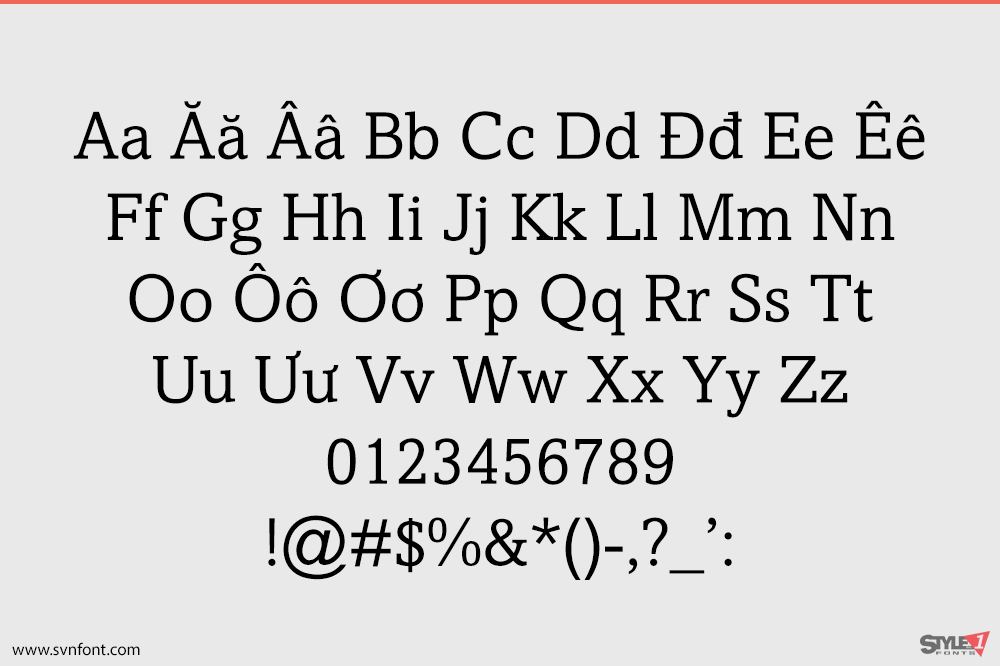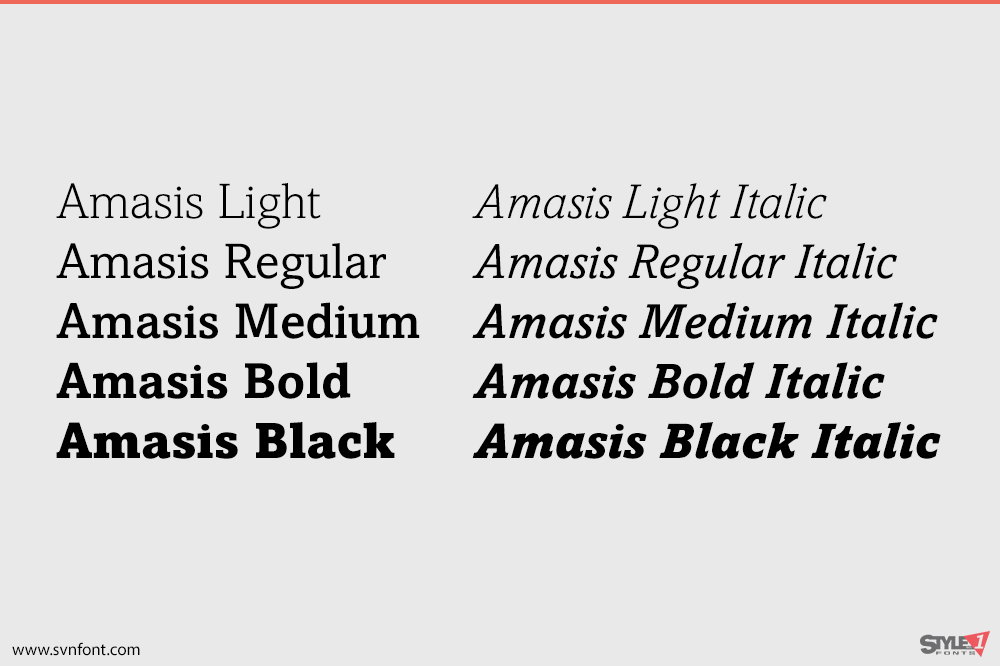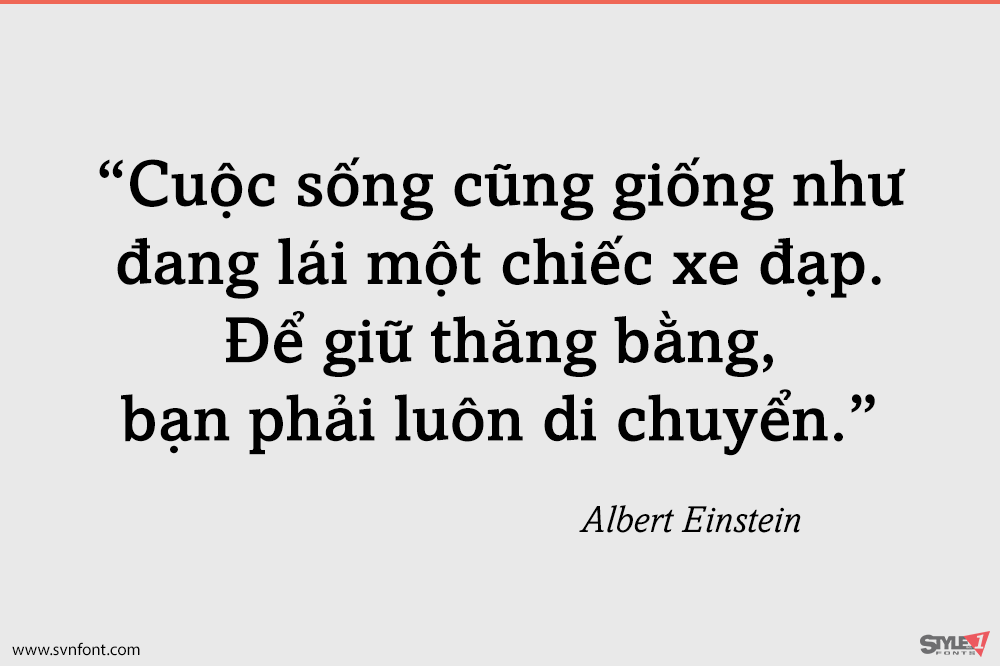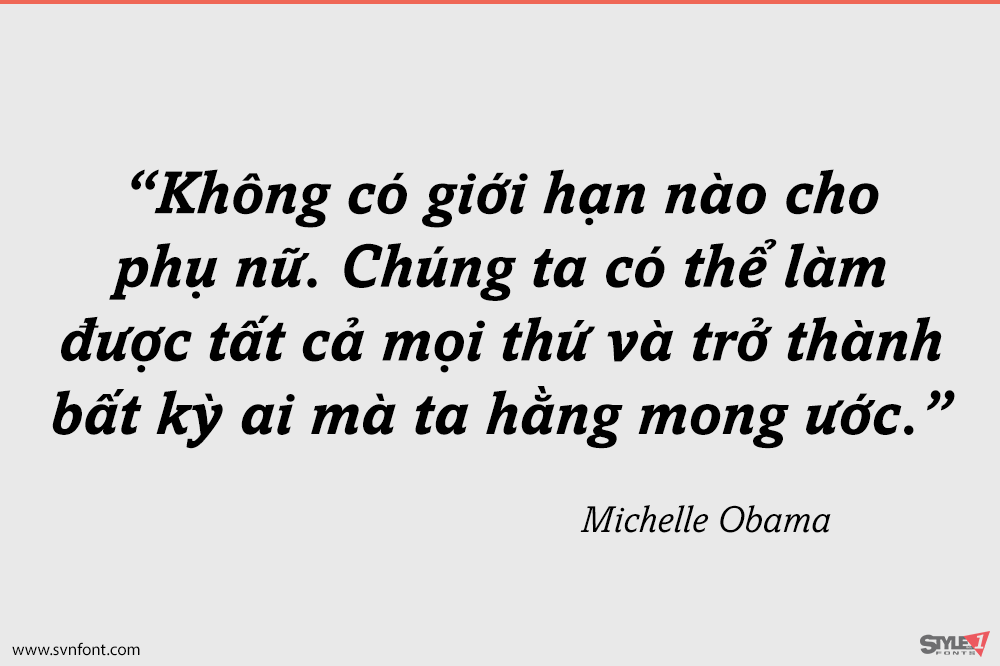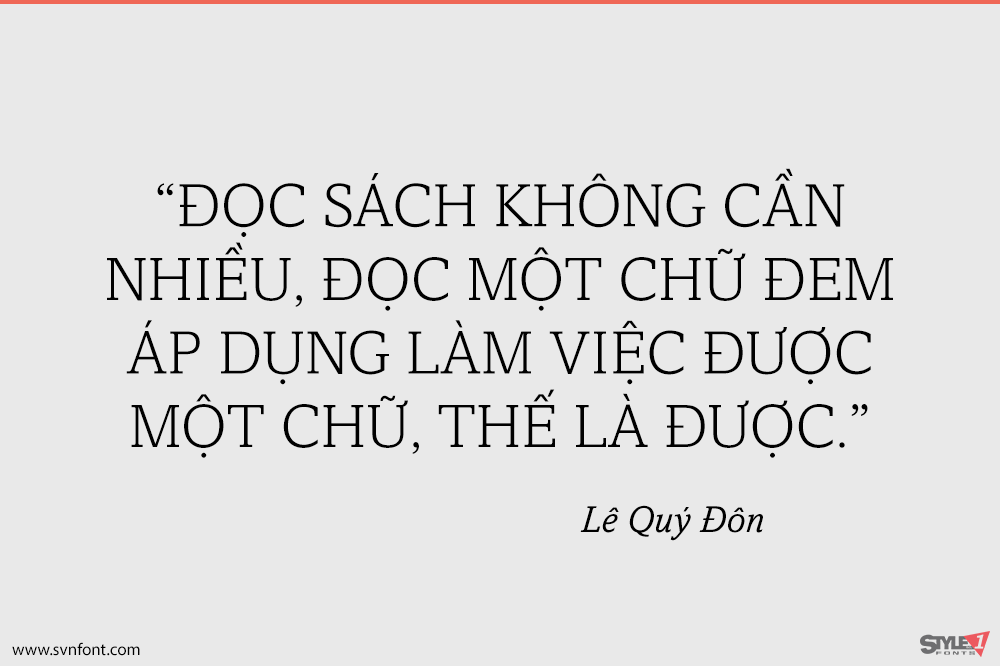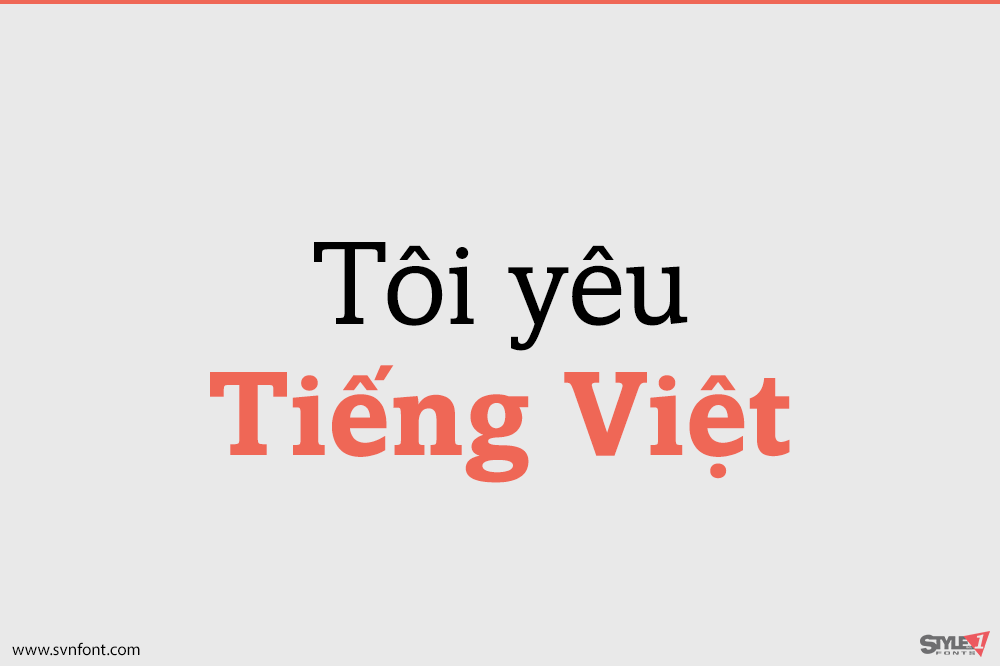
Bộ phông chữ Amasis™ là một thiết kế slab serif, được thể hiện với phong cách nhân văn bởi nghệ sĩ đồ họa và nhà thiết kế kiểu chữ người Anh nổi tiếng Ron Carpenter. Vẻ ngoài gần như công nghiệp của nó vẫn giữ được nét thanh lịch tinh tế: một sự kết hợp khá khó để đạt được.
Nhà thiết kế: Ron Carpenter
Nhà phát hành: Monotype